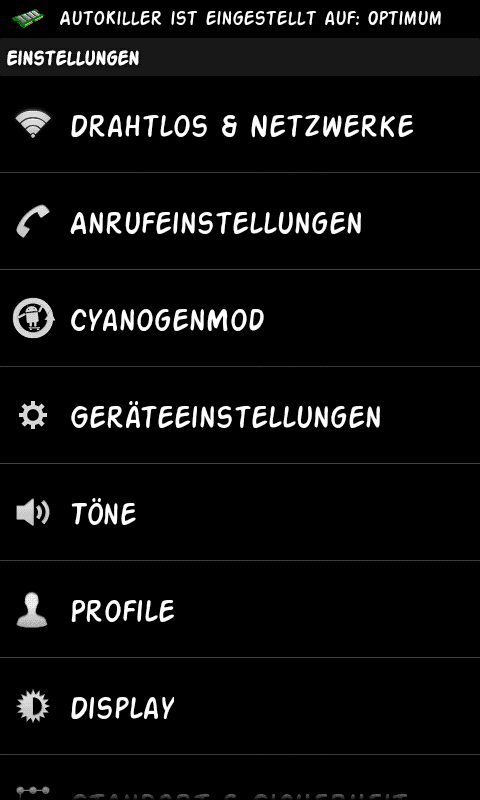
Schriftart (~Font) ändern
Hallo forum vielleicht kann mir jemand helfen ? und zwar wo kann ich die schrift art ändern beim samsung galaxy note ? Und gibt es eine app womit man mehr schrift arten haben kann ?
Einstellungen, Anzeige, Bildschirm und dann findest es.
Danke wieder was zum spielen. Die Schrift macht mehr aus als ich dachte.sieht aus wie ein neues Handy:scared:
Bei Samsung-geräten kann man sogennnte Flipfonts als neue Systemschriften installieren.
Neben den schon oben genannten Fontomizer gibt es auch professinelle Schriften von Monotype, einem traditionellem Schriftenhaus. Die sind zwar nicht für lau, aber gut.
Ich nutze Syndor als Flipfont. Ist schön und gut lesbar.
Hallo kennt jemand vielleicht eine App mittels der ich die Schriftart "action men" herunterladen kann?
Gibt es für die Schriftart eine App im Playstore womit man das direkt auf dem Smartphone installieren kann?
Also ich hab keine gefunden.
Geht mit Font Changer und einem gerooteten Handy.
Das einzige was du machen könntest wäre z.B. mit dem GoLauncherEx die Schriftart zu verwenden, die Einstellungsmenüs deines Handys bleiben natürlich in der System-Schriftart. Ohne Root ist die Schriftart nicht global zu ändern.
Habe den Root-Account noch nicht aktiviert und möchte das nicht machen weil ich keine Ahnung davon habe. Dachte es gäbe vielleicht eine App dafür. Ich hätte die Schrift so gerne.
Genau mit dem Go Launcher EX kannst die Schriftart ändern.
Und wo finde ich im Launcher die Schriftart action men?
Bei meinem S" habe ich zum Beispiel die "com.monotype.android.font.helveticaneue.apk" installiert, indem ich einfach die .apk ausgeführt habe. Diese Schriftart ist besonders eng, damit nichts abgeschnitten wird.
Kann ich diese Schriftart auf dem S3 auch einfach installieren, ohne dass mir irgendwas "zerstört" wird ?
Ja kannst du, FlipFonts funktionieren auf jedem Handy, das diese unterstützt.
Hab die Font installiert, und funktioniert !!